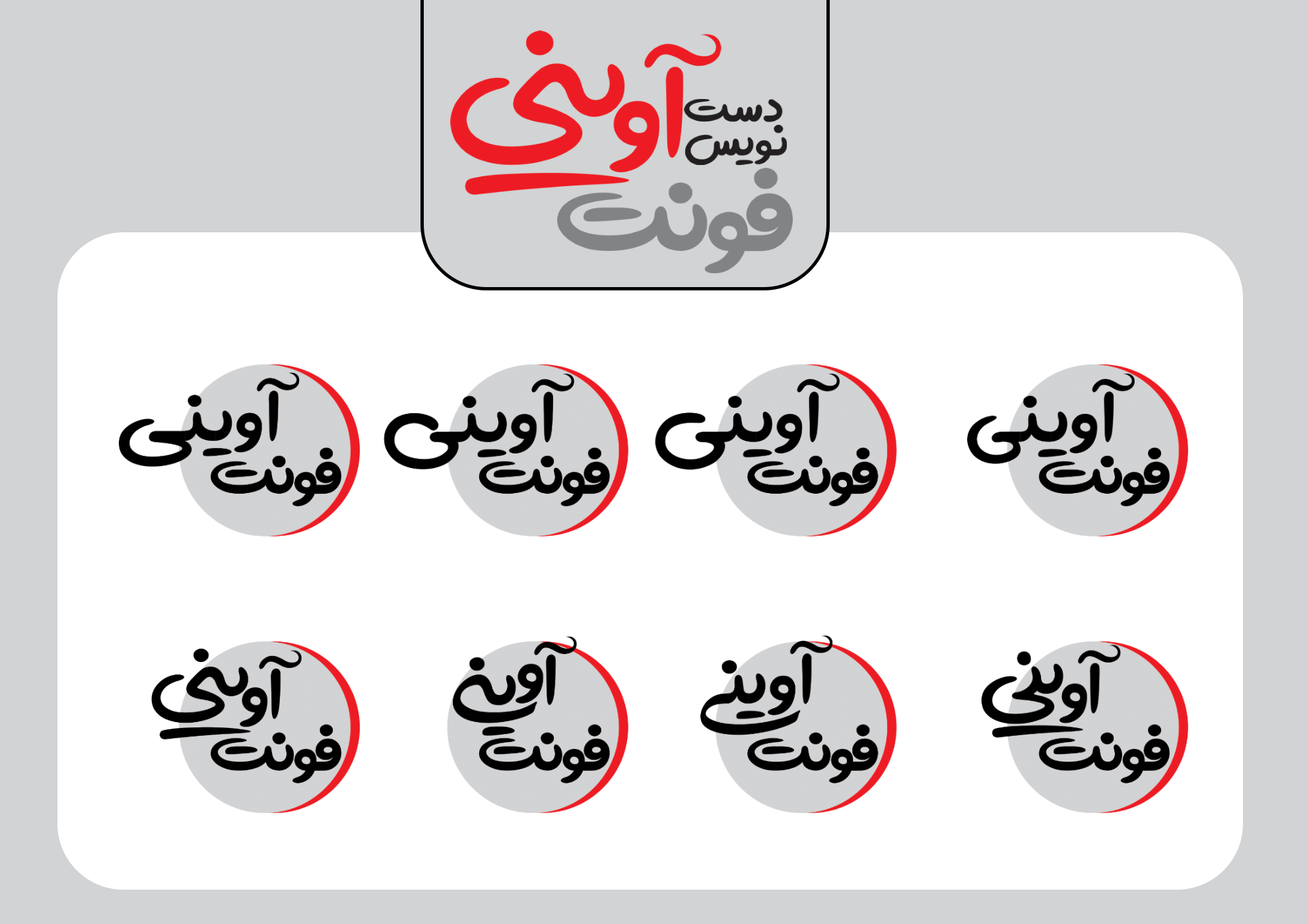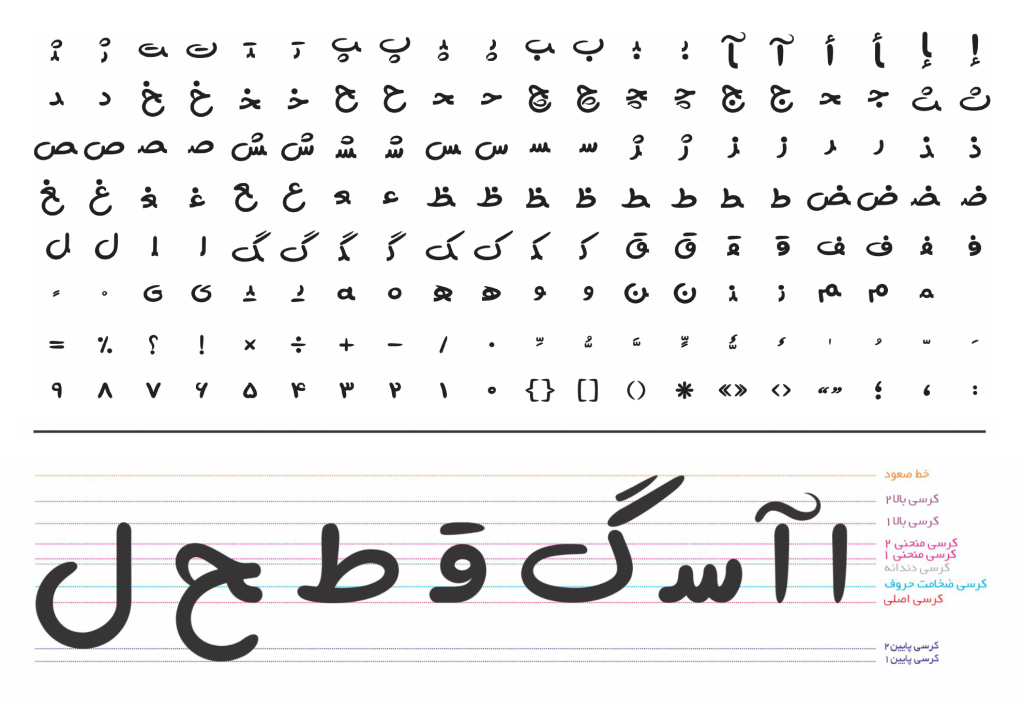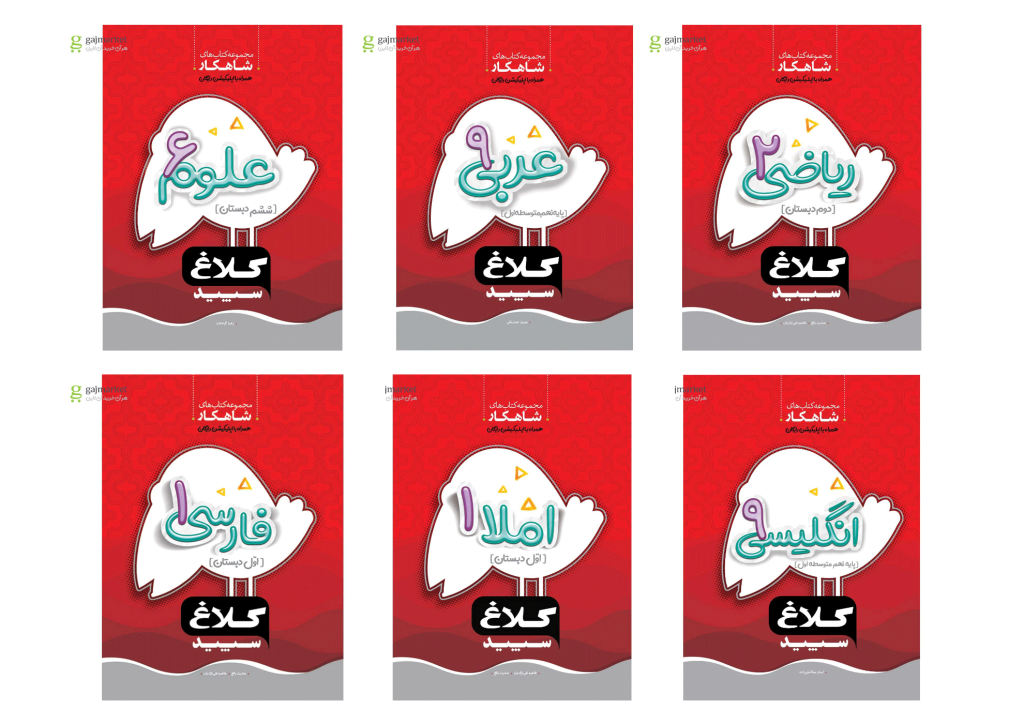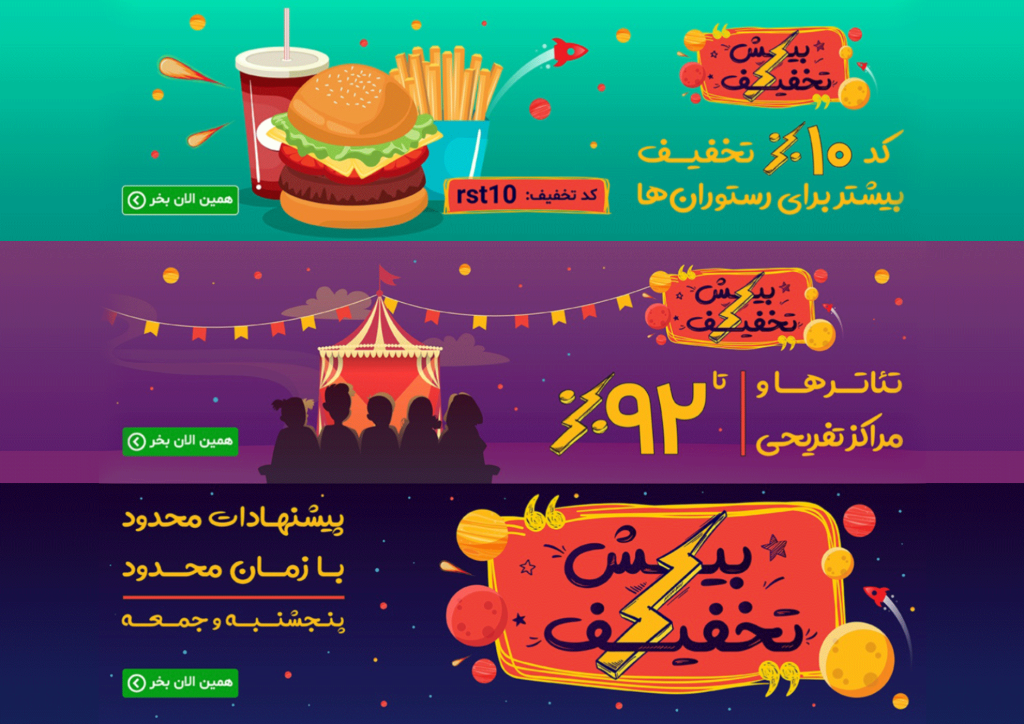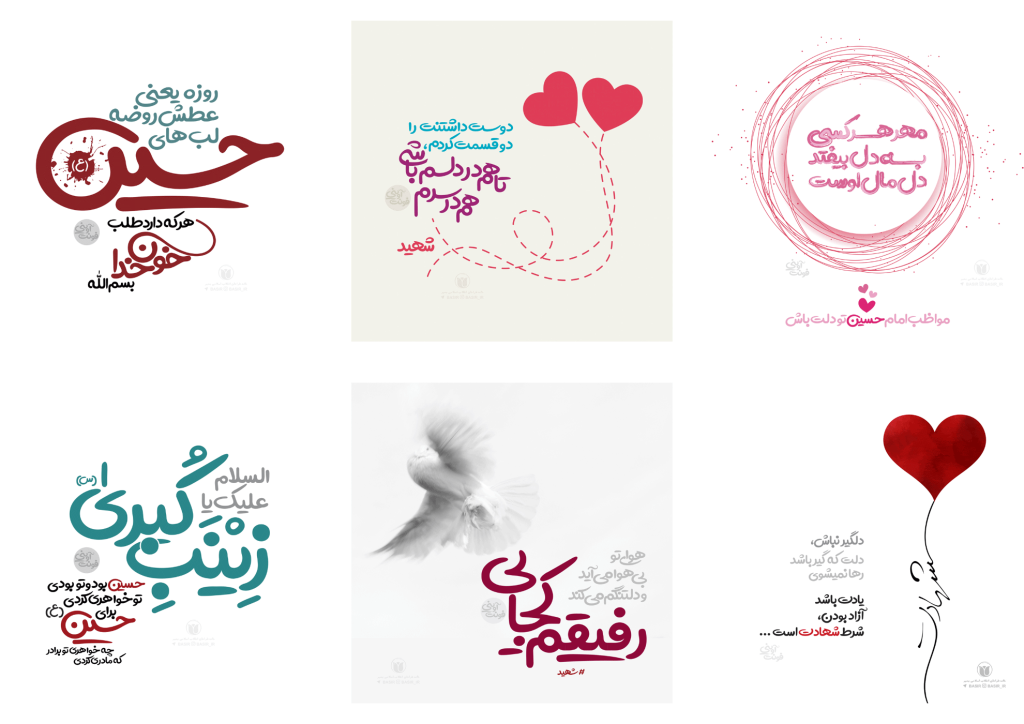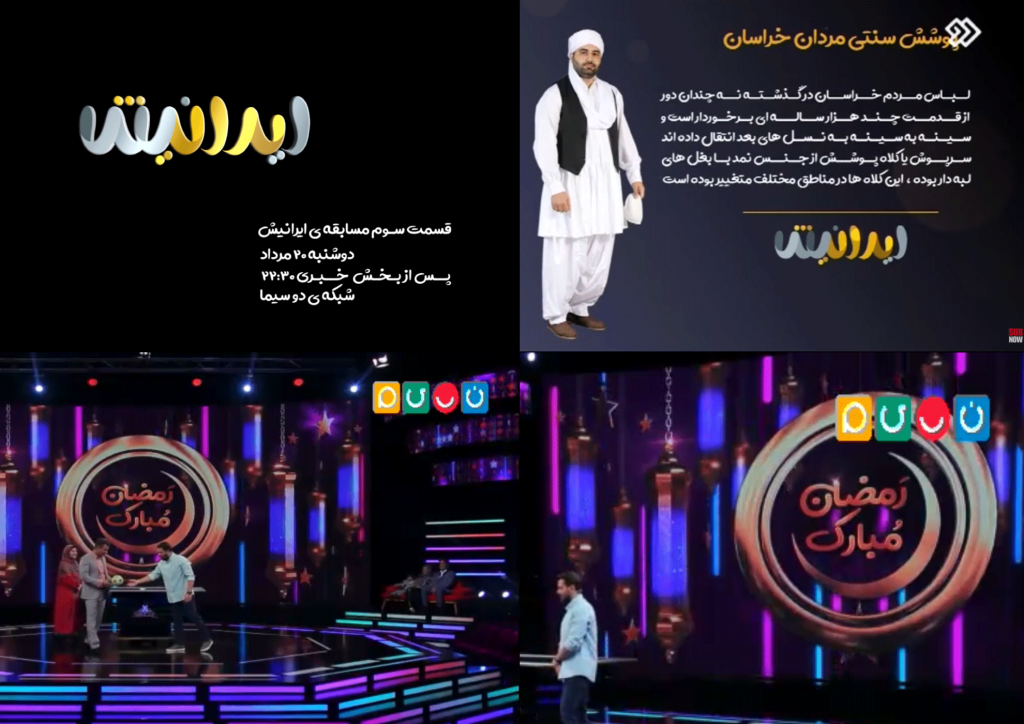
فونت آوینی
فونت اوینی تایپ فیسی دست نویس با روحیه فانتزی می باشد . در طراحی فرم ها و حروف این تایپ فیس از ابزار و قلمی روان وساده استفاده گردیده است و تا حد امکان از شکستگی ها و زوایای تند و تیز استفاده نشده به همین جهت حس سادگی و صمیمیت را به نگاه خوانندگان متبادر می کند.
از نقطه نظر هم خانوادگی و شباهت در فرم های طراحی فونت کتیبه نزدیک به قلم آوینی است. با این تفاوت که منسجم بودن ترکیبات در آوینی در مقایسه با کتیبه بیشتر می باشد. آوینی با روحیه جوان پر تحرکی که دارد مناسب انواع طراحی ها از دنیای وب و دیجیتال گرفته تا صنعت نشر و چاپ می باشد.
ترکیبات جایگزین در تایپ فیس آوینی
استفاده از حروف و ترکیبات جایگزین حس تنوع و زیبایی بیشتر را به نوشته ها و طراحی ها ارائه می دهد. در این تایپ فیس با کثرت و فراوانی حروف و ترکیبات جایگزین مواجه هستیم که سبب خلق نوشته ها پوستر ها تیتر ها و در یک کلام طراحی های کاملا متفاوت با استفاده از یک نوع از حروف فارسی می شود.